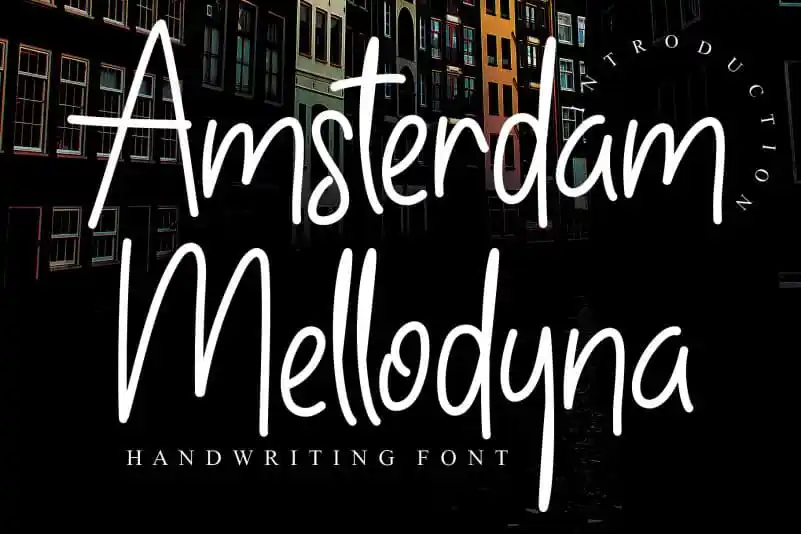
Amsterdam Mellodyna Handwritten Font – Download Grátis
Esta fonte é perfeita para os criativos que desejam dar um toque pessoal a seus projetos digitais. Intitulada ‘Amsterdam Mellodyna Handwritten Font’, ela se destaca como uma opção elegante e especial para designers gráficos, blogueiros e até mesmo streamers no YouTube. Fundamentada na autêntica mão do designer creativeletter, esta fonte transmite um sentimento pessoal e único através de sua escrita fluida e delicada. Adaptar texto em uma fonte handwritten é sempre uma maneira criativa de personalizar sua marca ou projeto. A ‘Amsterdam Mellodyna Handwritten Font’ oferece precisão e flexibilidade, permitindo que você personalize seu design sem perder a autenticidade da escrita. Com um design suave e levemente ondulado, ela é ideal para aplicações como postagens de redes sociais, blogs pessoais ou designs digitais onde queremos destacar o toque pessoal. Já imaginou seus conteúdos em um texto que parece ter saído da própria mãos? Esta fonte convida você a experimentar um novo e fascinante método para expressar sua identidade digital. Aproveite ao máximo este designer handwritten, ele traz uma personalização única e especial a qualquer projeto que você lance.